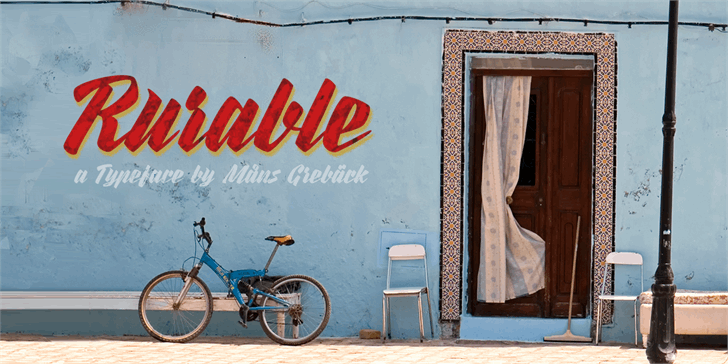
Rurable font – Fonte Grátis
Rurable font
A Rurable é uma elegante fonte script desenvolvida pelo designer Hamilton para quem busca um estilo fluido e versátil que se encaixa perfeitamente tanto no design editorial quanto na tipografia corporativa. Com linhas arredondadas, gestos harmoniosos e acabamento cuidadosamente criado, esta fonte é uma escolha incrível para aplicativos em que o equilíbrio gráfico faz toda a diferença. Concebida para manter o brilho da natureza na sua interface ou criação de layouts, Rurable transmite um encanto natural e profundo. Seja você designer gráfico, editorialista ou criador de sites, esta fonte script proporciona um toque autêntico que se encaixa perfeitamente em qualquer projeto. Para aqueles que buscam uma fonte versátil com um estilo único, a Rurable é definitivamente para você. Visite o site da Mans Greback para obter mais informações sobre licenciamento comercial.